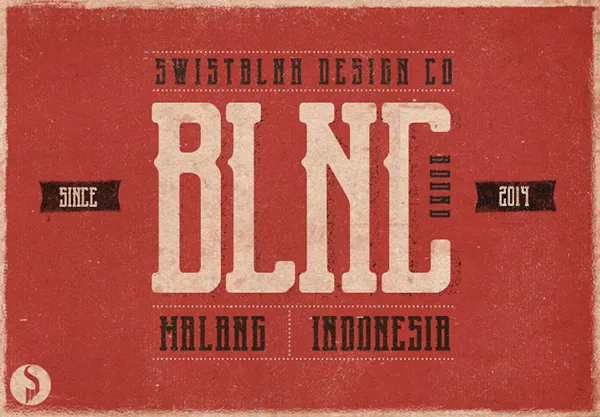
A Blnc Round Font é uma escolha perfeita para quem busca estilos modernizados com um toque vintage na sua designação de texto. Esta família fonte, que inclui cinco pesos (Regular, Round, Rough, Dust e Vintage), foi criada por Swistblnk Design Std. Inspirado em letra western antiga com uma pitada moderna, a Blnc Round é adequada para diversas necessidades de desenho, desde headlines até rótulos e logos. Para os amantes do estilo vintage que adoram letras aquarelas ao mesmo tempo, a Blnc oferece um toque vintage junto com um pouco de poeira para dar uma sensação ainda mais manuscrita. Esta fonte não apenas complementa seu design em qualquer aplicação visual, mas também adiciona um toque único e sofisticado à sua criação. Ideal para aquelas ocasiões que exigem um touch a mais de singularidade no seu trabalho grafico. A Blnc é uma opção perfeita tanto para projetos profissionais quanto para trabalhos pessoais, oferecendo um design moderno com um toque nostálgico inconfundível.